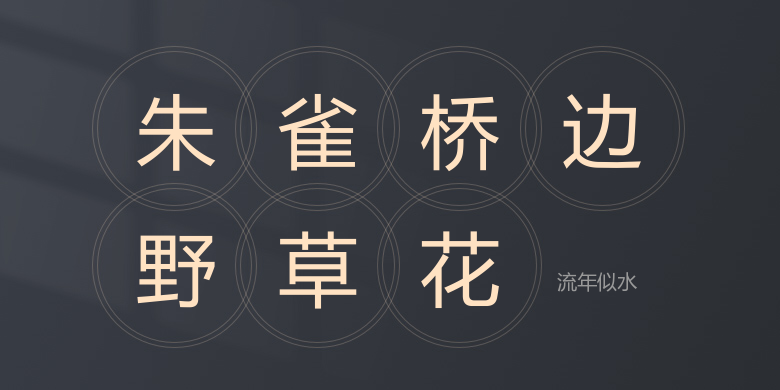
流年似水
流年似水,这款字体结构工整、笔画清晰,兼顾美观与易读性,适用于标题、正文、海报、包装、LOGO 等多种场景。字形优雅稳定,风格百搭耐看,适配日常排版与创意设计,让文字呈现更舒适、更具质感。流年似水一笔一画,皆是细节,以均衡的比例、流畅的线条打造舒适视觉体验,字形端正大气,风格简约现代。无论是商业设计、品牌宣传还是日常排版,都能轻松驾驭,让文字更有格调与力量。流年似水字体下载。